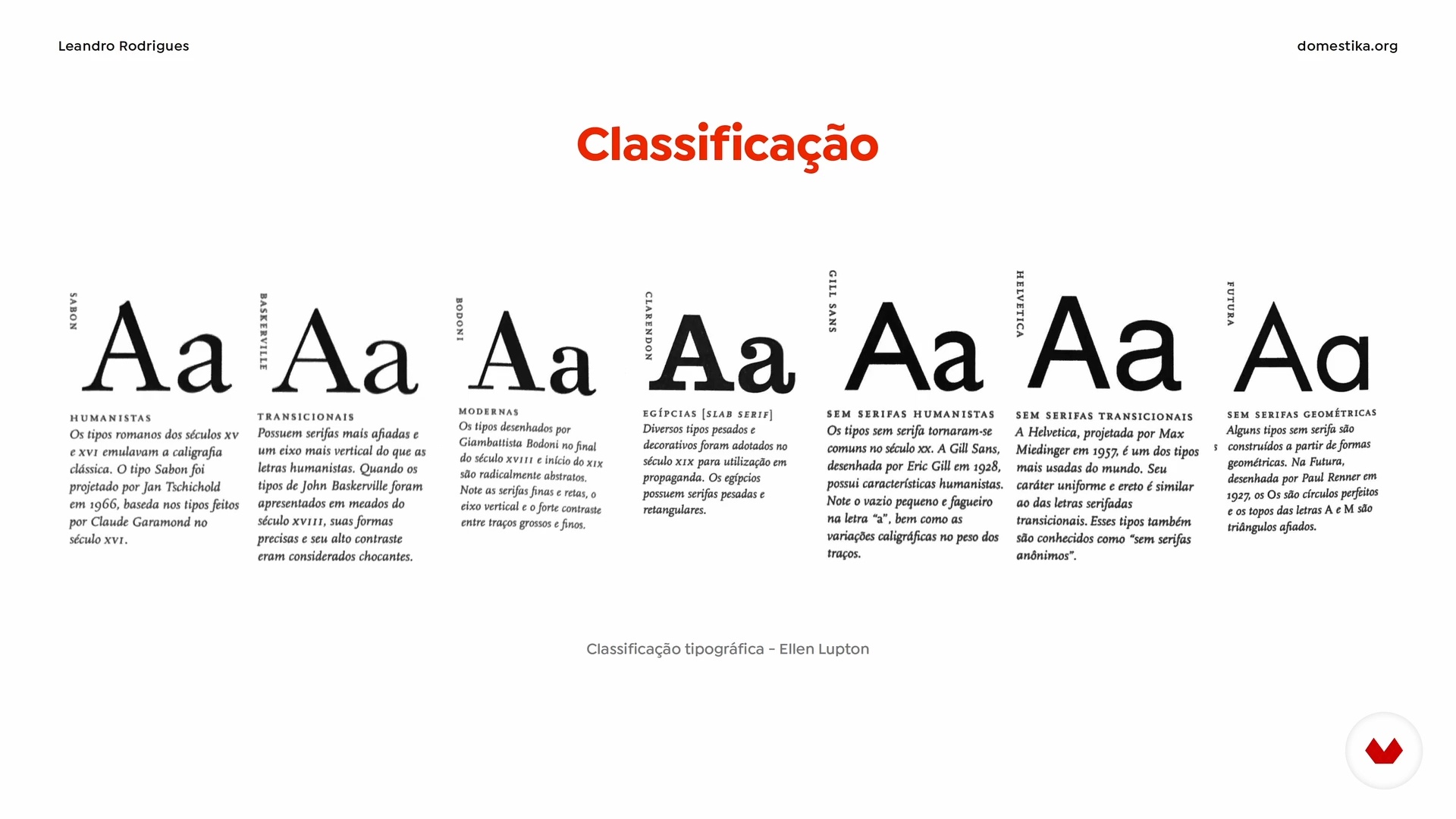
Typographie pour des projets numériques et imprimés
Classification et catégorisation typographique
À propos de la leçon : Classification et catégorisation typographique
“Dans cette classe, vous verrez comment nous pouvons catégoriser et classer les polices pour mieux comprendre les fonctions pour lesquelles elles ont été créées et en tirer parti. ”
Dans cette leçon, Leandro Rodrigues aborde le sujet : Classification et catégorisation typographique, qui fait partie du cours Domestika en ligne : Typographie pour des projets numériques et imprimés. Apprenez à sélectionner, combiner et styliser des polices de caractères pour des titres, des sous-titres et des textes longs et à mettre en page vos publications.
“Classification et catégorisation typographique Dans cette leçon, nous verrons comment catégoriser les polices selon leurs fonctions et leurs styles. Conceptuellement, la typographie est liée à la calligraphie et au lettrage. La calligraphie est une technique manuelle dans lequel un mouvement unique et fluide est utilisé pour, avec le moins de traits possible, créer des lettres. Il est basé sur les styles ou des modèles historiques de conception de lettres, soit en leur obéissant, soit en les renversant. Il valorise l'aspect esthétique, mais aussi celui de la lisibilité. Le lettrage est une ...”